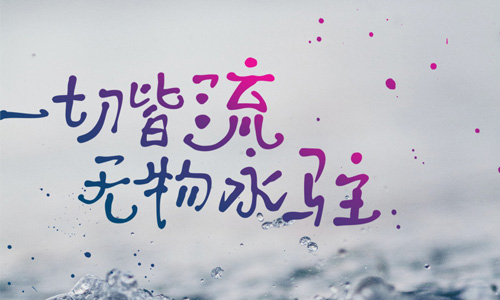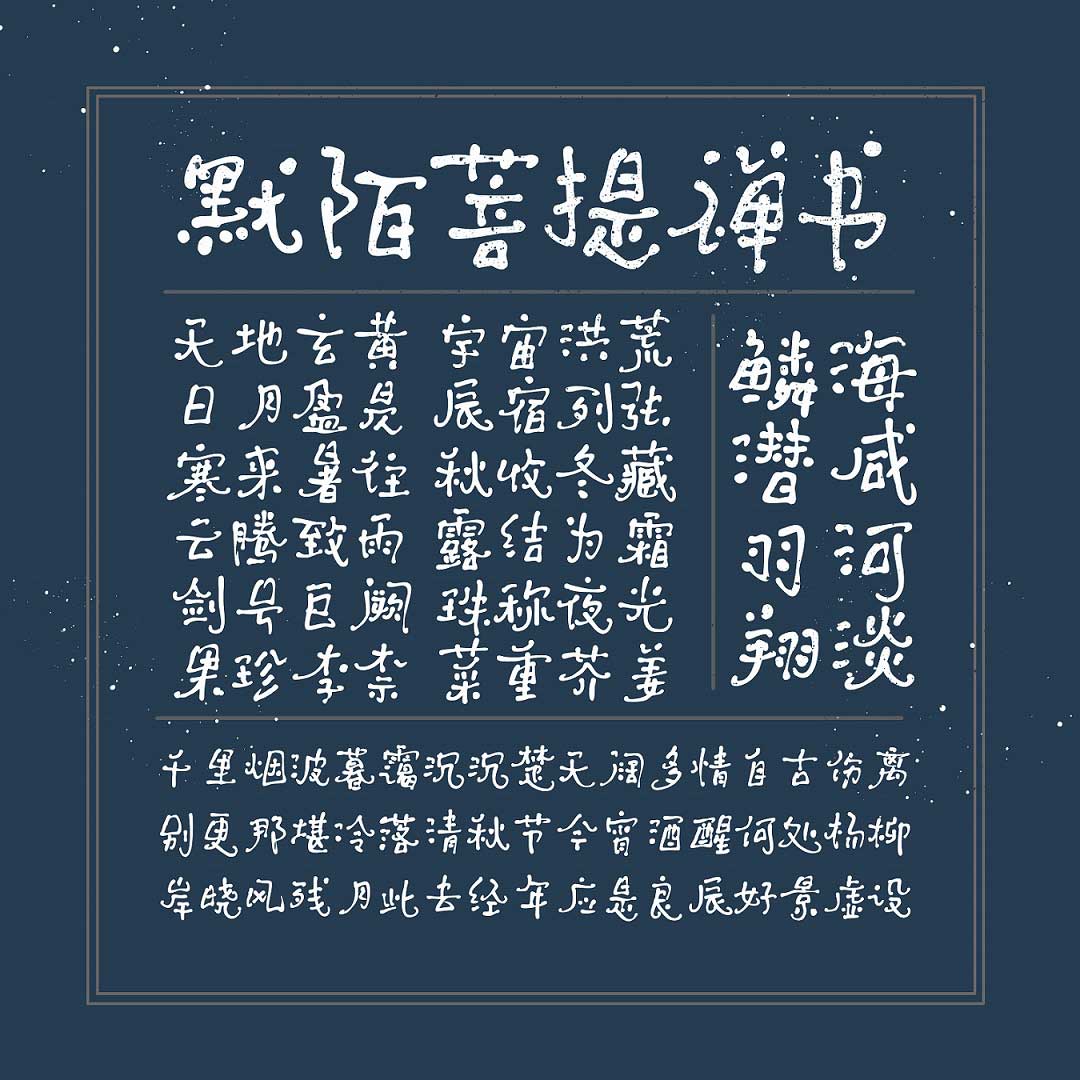
默陌菩提禪書(shū)字體是默陌字庫(kù)最新推出的一款極具個(gè)性的書(shū)法藝術(shù)字體,字形靈動(dòng)多姿,筆畫(huà)卷曲如枝,字體結(jié)構(gòu)舒展松弛,筆末曲折飄逸,賦予字體蒼勁中不乏妖冶的古典氣質(zhì),適用于影視廣告、海報(bào)、個(gè)性化排版等多種場(chǎng)景應(yīng)用,歡迎喜歡默陌菩提禪書(shū)字體的朋友前來(lái)下載使用。